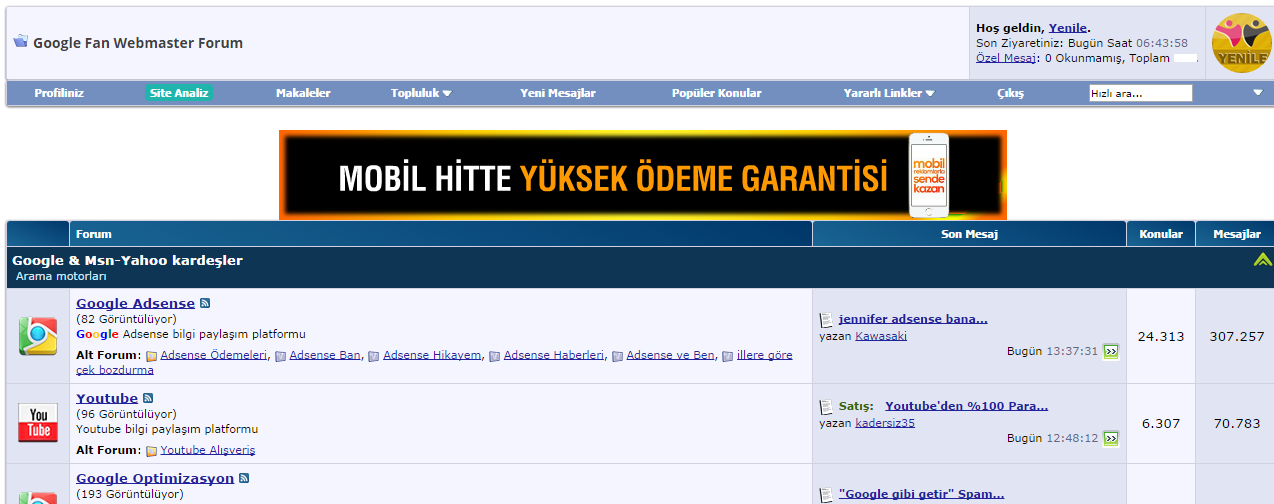
Chrome bugün güncellendi bende yazı tipi değişti, üstün bir değişiklik yok ama Google fontlardan birine geçti sanırım. r10 da kategoriler altındaki çizgiler harflere çok yaklaştığı için hoş görünmüyor. Benzer durumda olan var mı?
Chrome Güncellendikten Sonra Yazı Tipi
- 04-09-2014, 14:35:05Adres çubuğuna; chrome://flags yazın.
Açılan pencerede DirectWrite'ı Devre Dışı Bırak seçeneğini Etkinleştir yapın ve yeniden başlatın.
Sorun düzelecektir. Akşam bende saatlerce uğraştım bunun için.